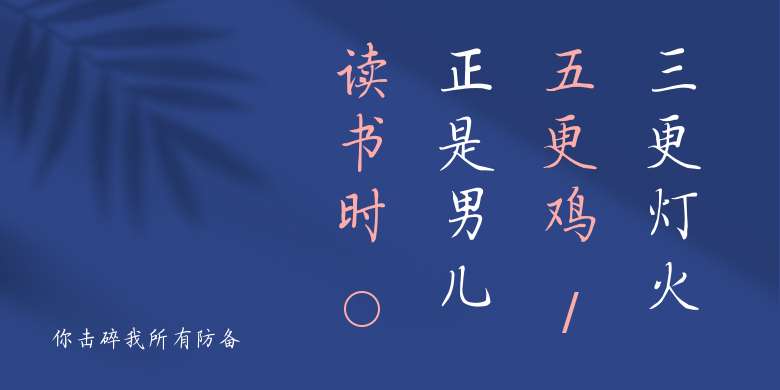
你击碎我所有防备
你击碎我所有防备,这款字体结构工整、笔画清晰,兼顾美观与易读性,适用于标题、正文、海报、包装、LOGO 等多种场景。字形优雅稳定,风格百搭耐看,适配日常排版与创意设计,让文字呈现更舒适、更具质感。你击碎我所有防备一笔一画,皆是细节,以均衡的比例、流畅的线条打造舒适视觉体验,字形端正大气,风格简约现代。无论是商业设计、品牌宣传还是日常排版,都能轻松驾驭,让文字更有格调与力量。你击碎我所有防备字体下载。